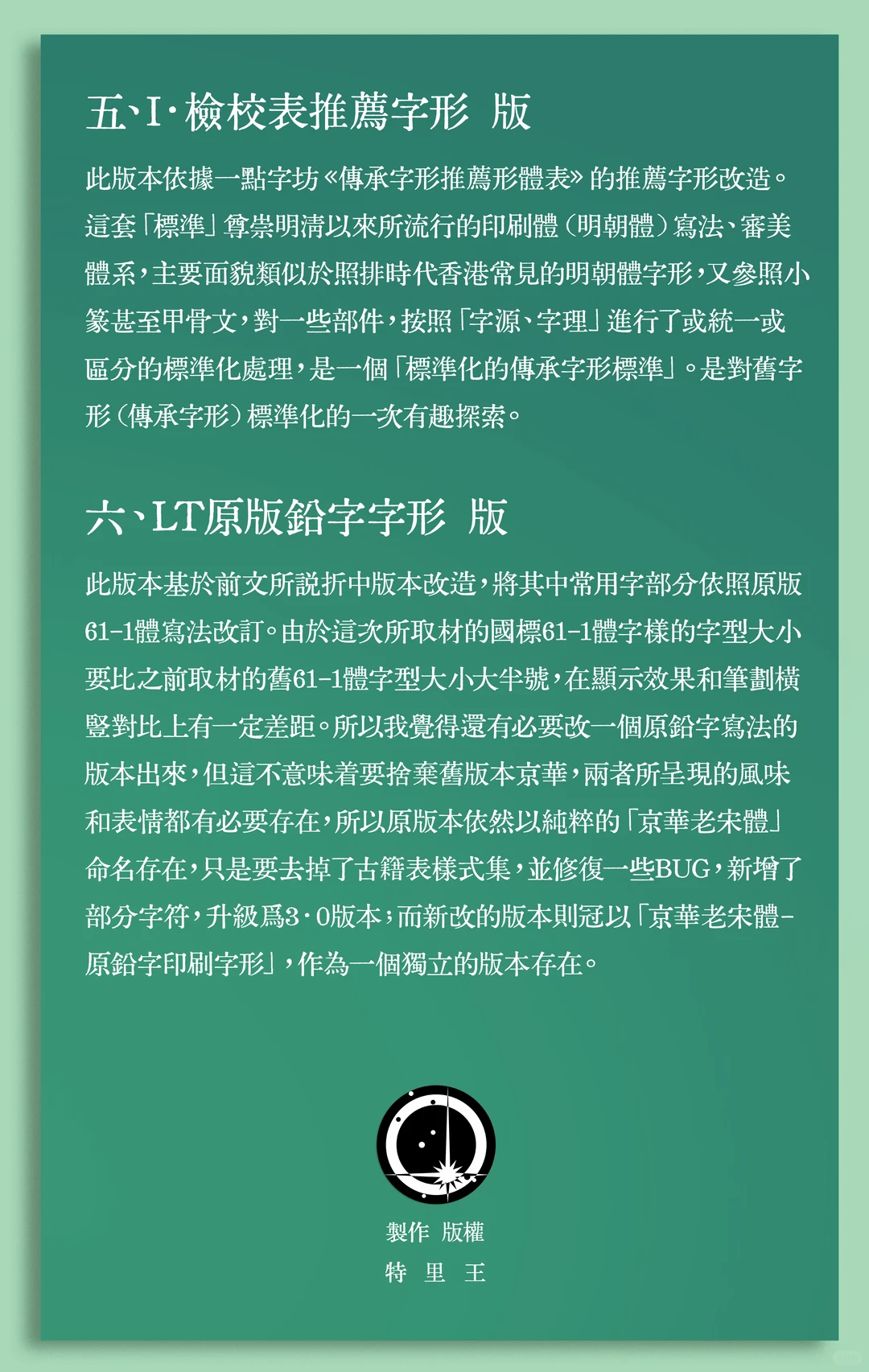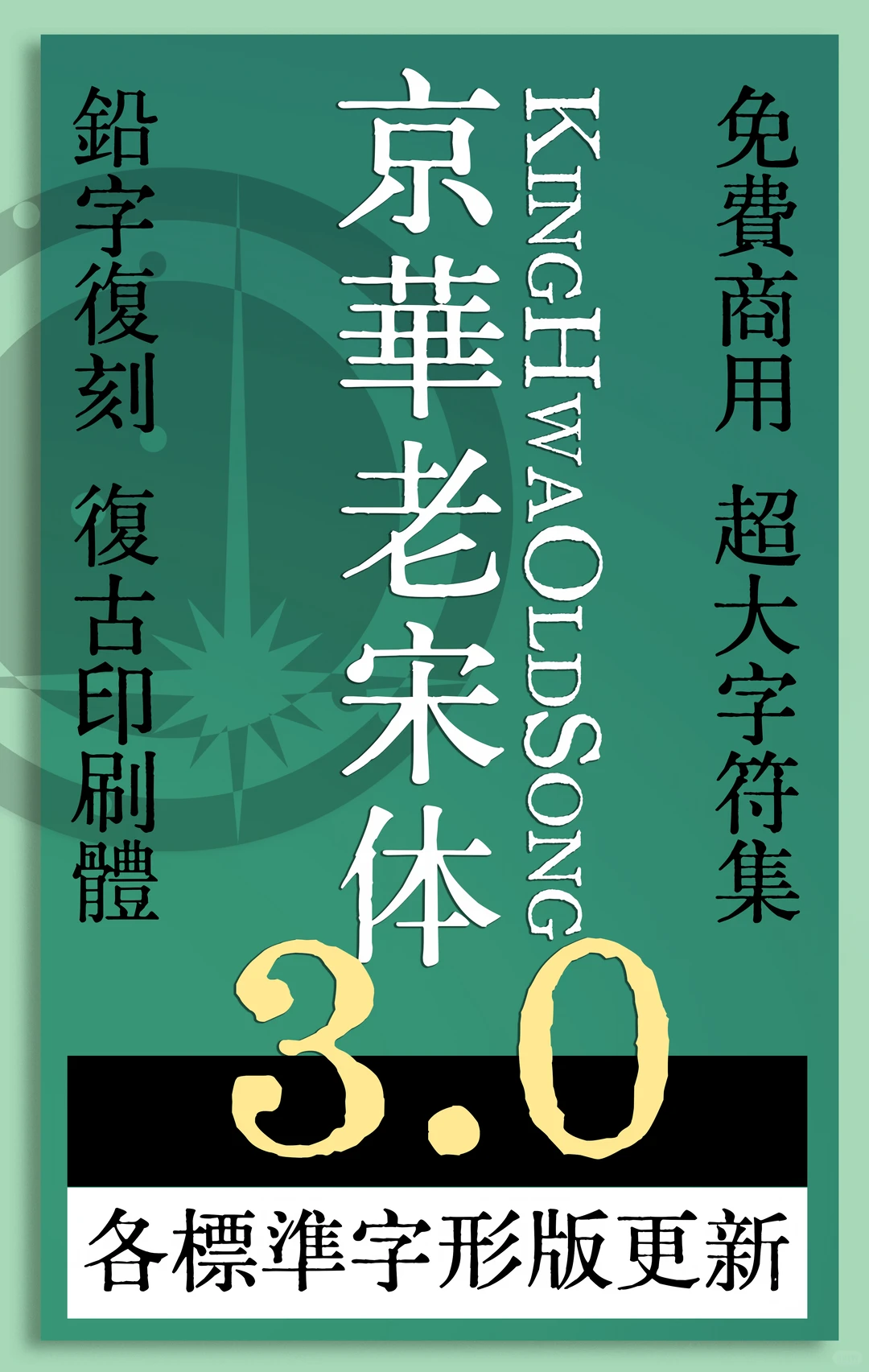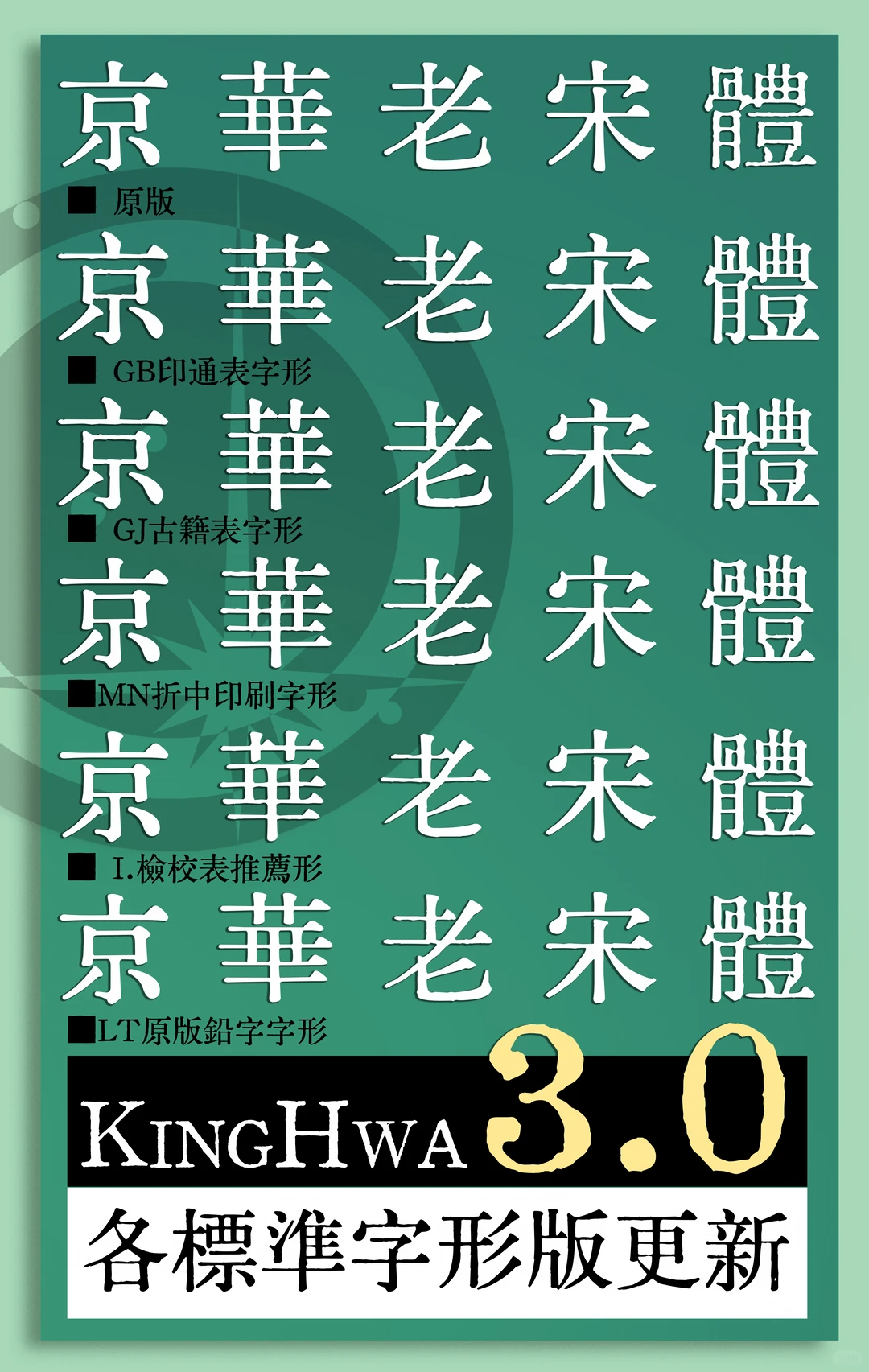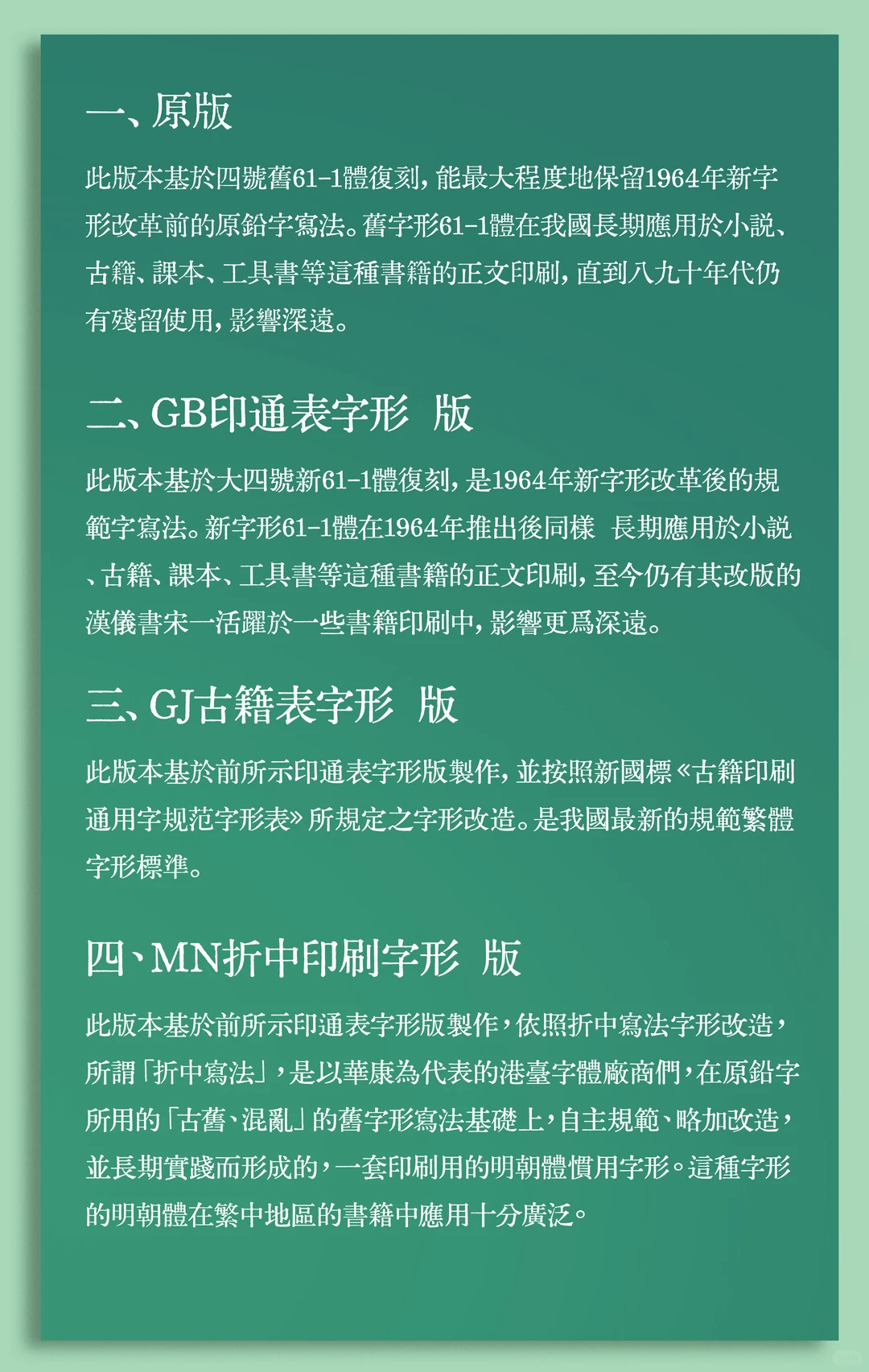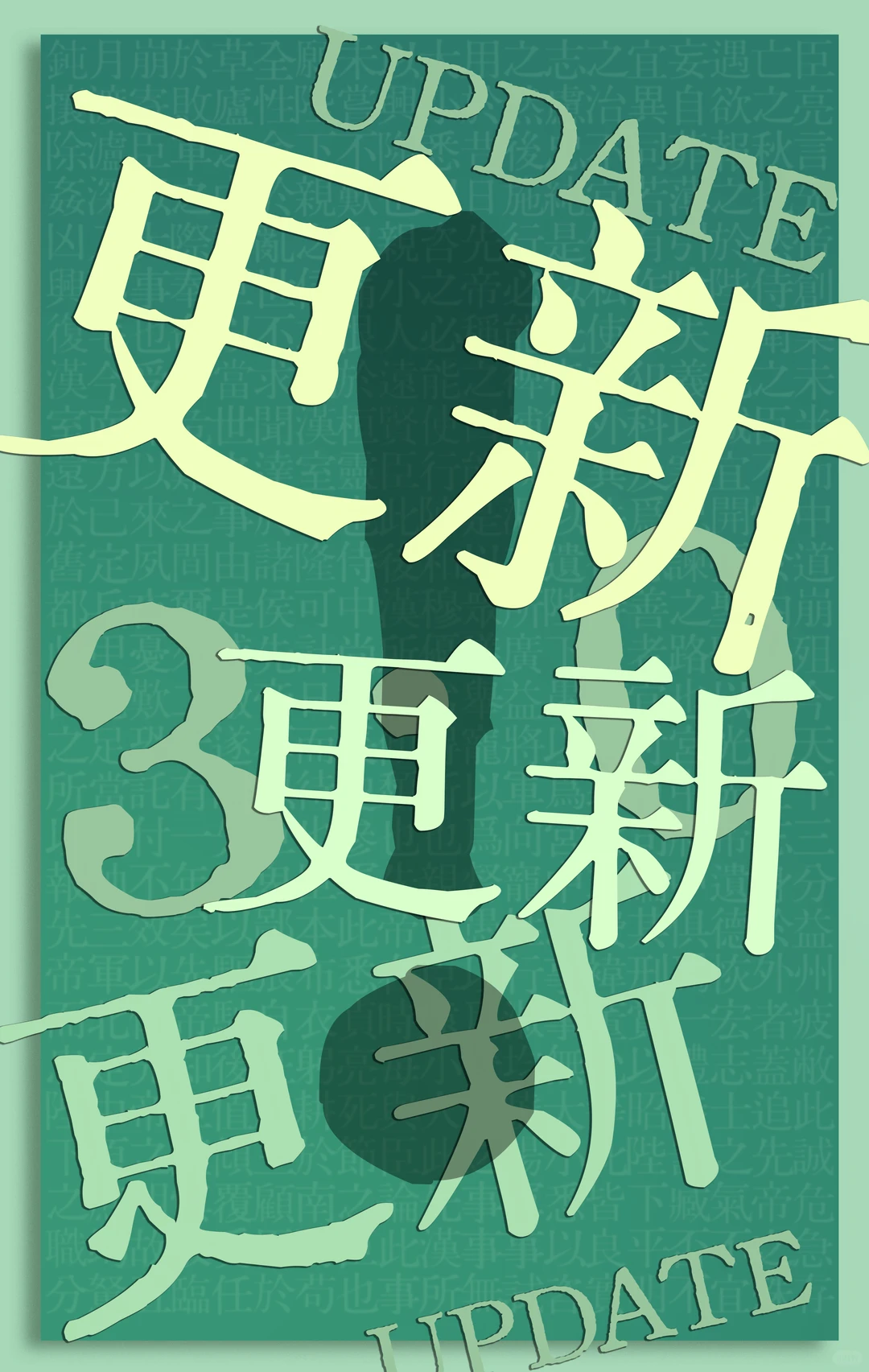
京華老宋体
一、原版
此版本基于四号旧61-1体复刻,能最大程度地保留1964年新字形改革前的原铅字写法。旧字形61-1体在我国长期应用于小说、古籍、课本、工具书等这种书籍的正文印刷,直到八九十年代仍有残留使用,影响深远。
二、GB印通表字形 版
此版本基于大四号新61-1体复刻,是1964年新字形改革后的规范字写法。新字形61-1体在1964年推出后同样 长期应用于小说、古籍、课本,工具书等这种书籍的正文印刷,至今仍有其改版的汉仪书宋一活跃于一些书籍印刷中,影响更为深远。
三、GJ古籍表字形 版
此版本基于前所示印通表字形版制作,并按照新国标《古籍印刷通用字规范字形表》所规定之字形改造。是我国最新的规范繁体字形标准。
四、MN折中印刷字形 版
此版本基于前所示印通表字形版制作,依照折中写法字形改造,所谓「折中写法」,是以华康为代表的港台字体厂商们,在原铅字所用的「古旧、混乱」的旧字形写法基础上,自主规范、略加改造,并长期实践而形成的,一套印刷用的明朝体惯用字形。这种字形的明朝体在繁中地区的书籍中应用十分广泛。
五、I检校表推荐字形 版
此版本依据一点字坊《传承字形推荐形体表》的推荐字形改造。
这套「标准」尊崇明清以来所流行的印刷体(明朝体)写法、审美体系,主要面貌类似于照排时代香港常见的明朝体字形,又参照小篆甚至甲骨文,对一些部件,按照「字源、字理」进行了或统一或区分的标准化处理,是一个「标准化的传承字形标准」。是对旧字形(传承字形)标准化的一次有趣探索。
六、LT原版铅字字形 版
此版本基于前文所说折中版本改造,将其中常用字部分依照原版61-1体写法改订。由于这次所取材的国标61-1体字样的字型大小要比之前取材的旧61-1体字型大小大半号,在显示效果和笔划横竖对比上有一定差距。所以我觉得还有必要改一个原铅字写法的版本出来,但这不意味着要舍弃旧版本京华,两者所呈现的风味和表情都有必要存在,所以原版本依然以纯粹的「京华老宋体」命名存在,只是要去掉了古籍表样式集,并修复一些BUG,新增了部分字符,升级为3•0版本;而新改的版本则冠以「京华老宋体-原铅字印刷字形」,作为一个独立的版本存在。收录范围
统一码基础汉字区:全收录
统一码扩展A区:全收录
古籍印刷通用字规范字形表:全收录
喃字常用字表:全收录
已编码二简字:全收录
京华老宋体3.0字体海报,铅字复刻复古印刷体,免费商用超大字符集,各标准字形版更新-刊刻Kntuk
京华老宋体3.0各标准字形版更新,对比展示原版、GB印通表、GJ古籍表、MN折中印刷、I.检校表推荐及LT原版铅字等字形。-刊刻Kntuk
这张图讲了四种字体版本,分别是保留老铅字写法的原版,1964年改革后的GB印通表字形版,按古籍新国标做的GJ古籍表字形版,还有港台常用的MN折中印刷字形版。-刊刻Kntuk
京华老宋体字体说明图,介绍了检校表推荐字形版和LT原版铅字字形版的设计依据,底部标注制作版权为特里王。-刊刻Kntuk
图片以蓝绿色为底,印有“UPDATE”和“更新”大字及数字“3”,背景有人影和模糊文字,表示第三次更新。-刊刻Kntuk